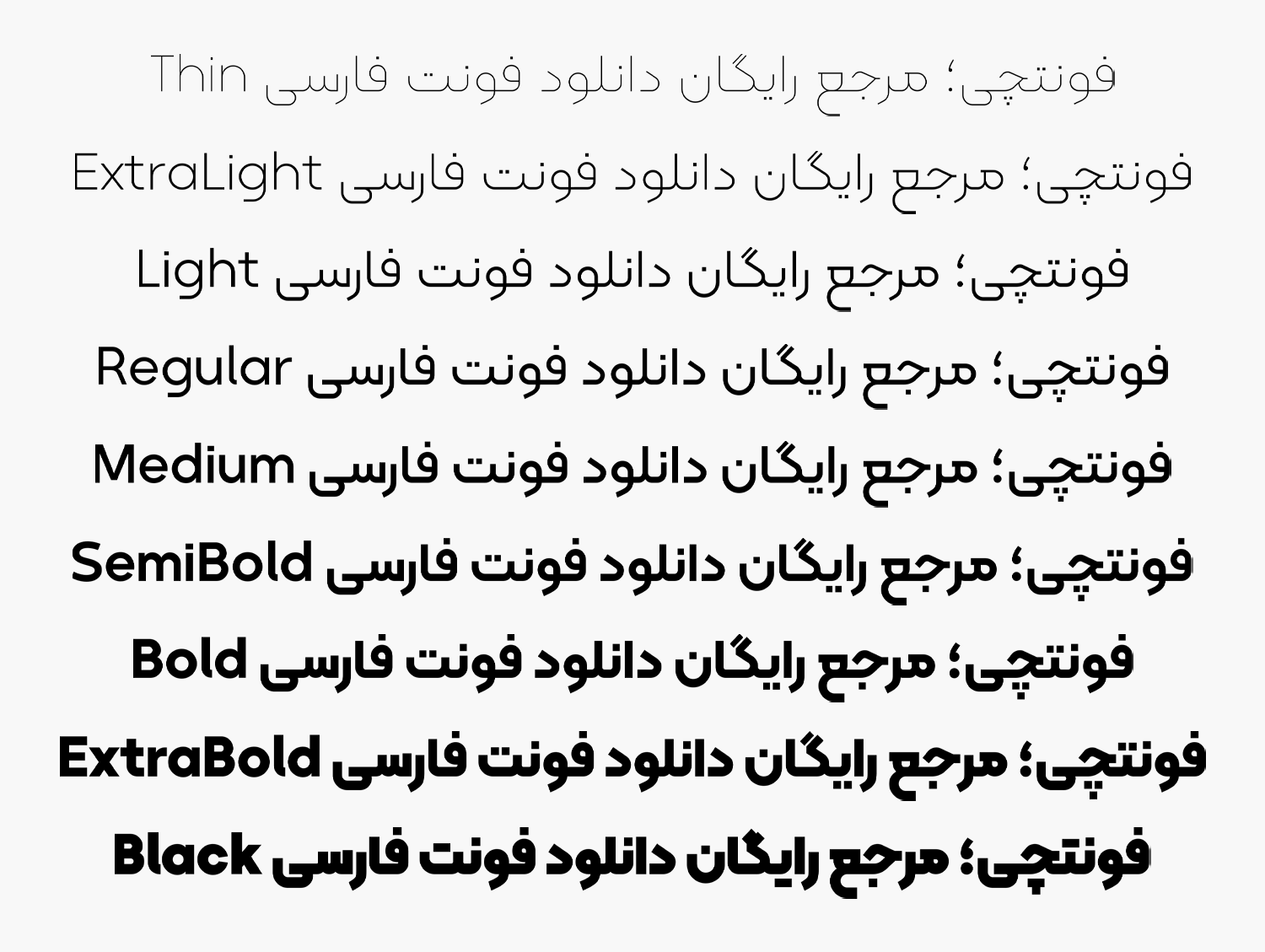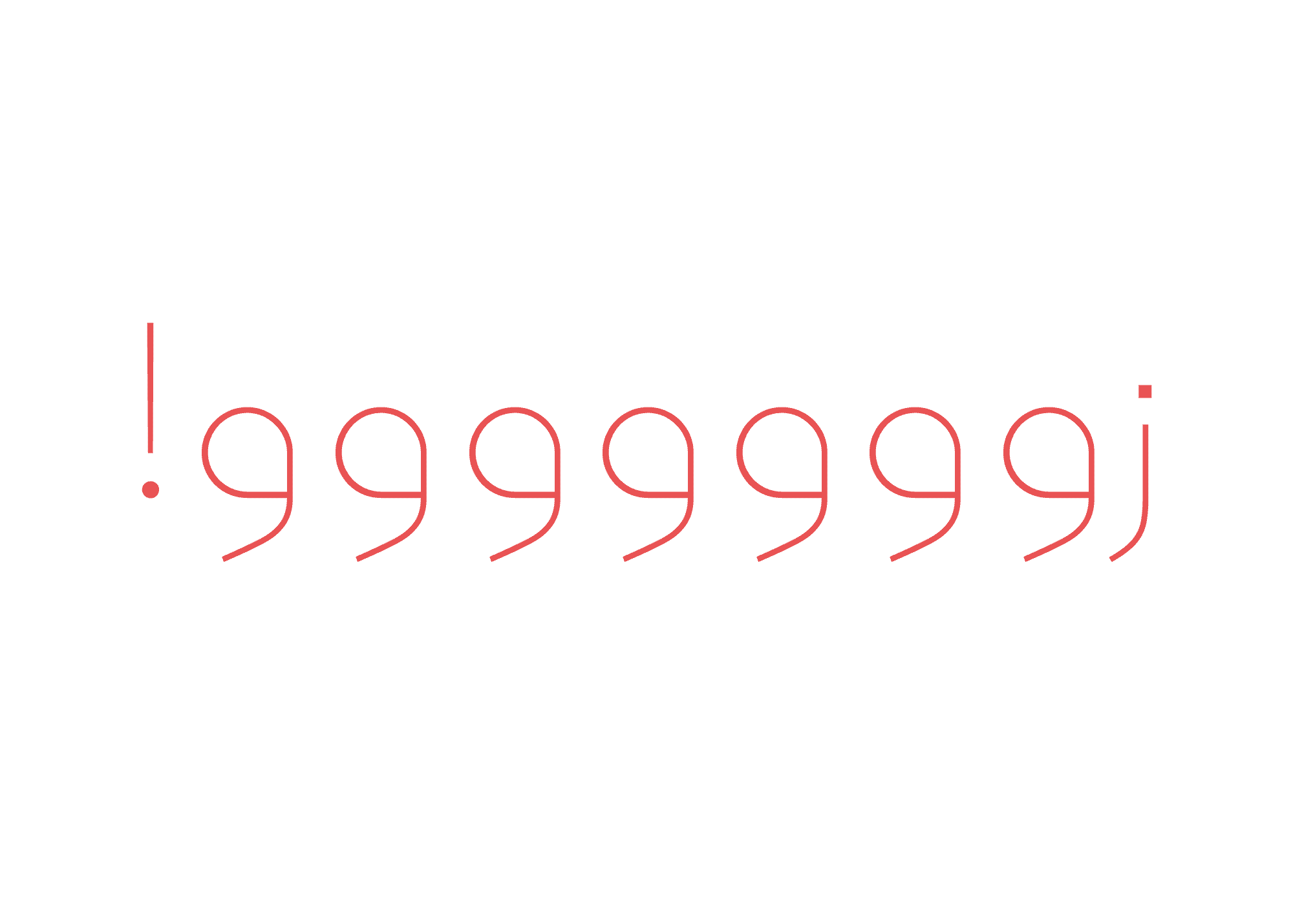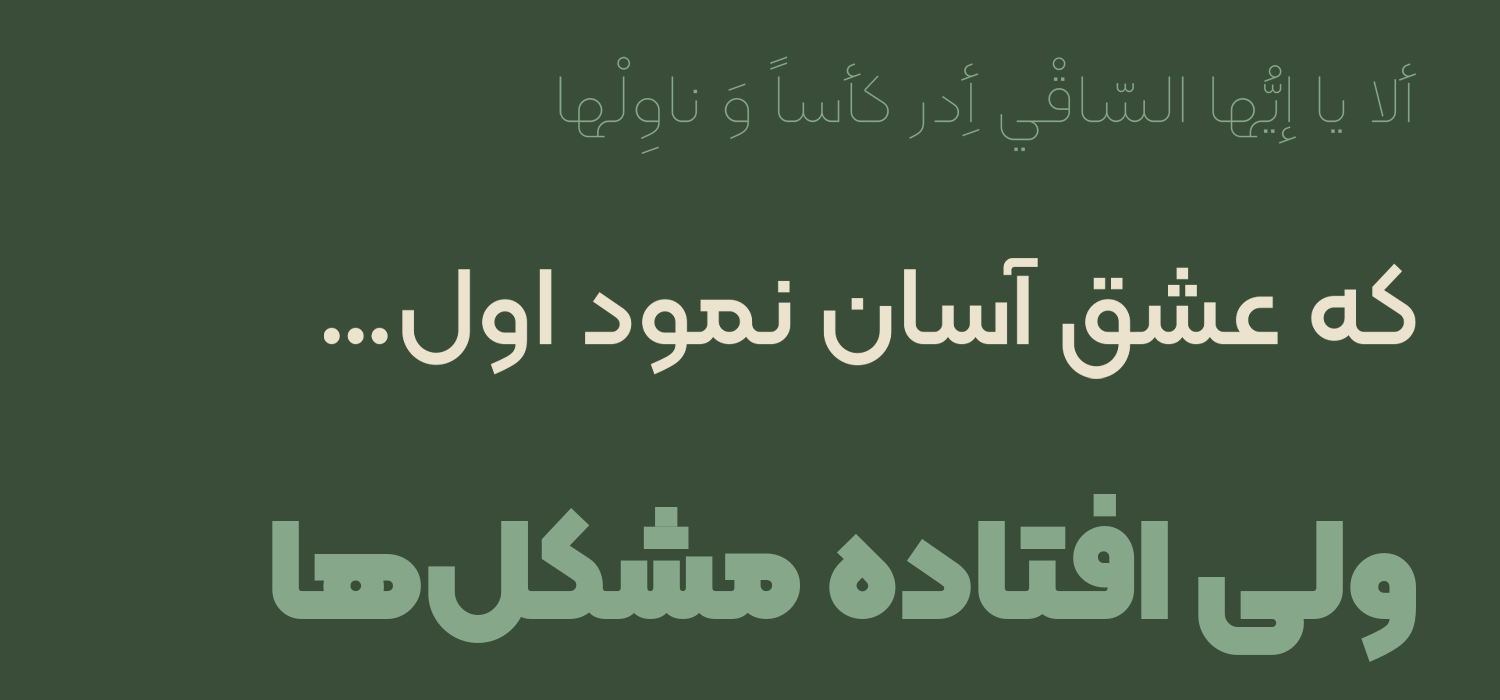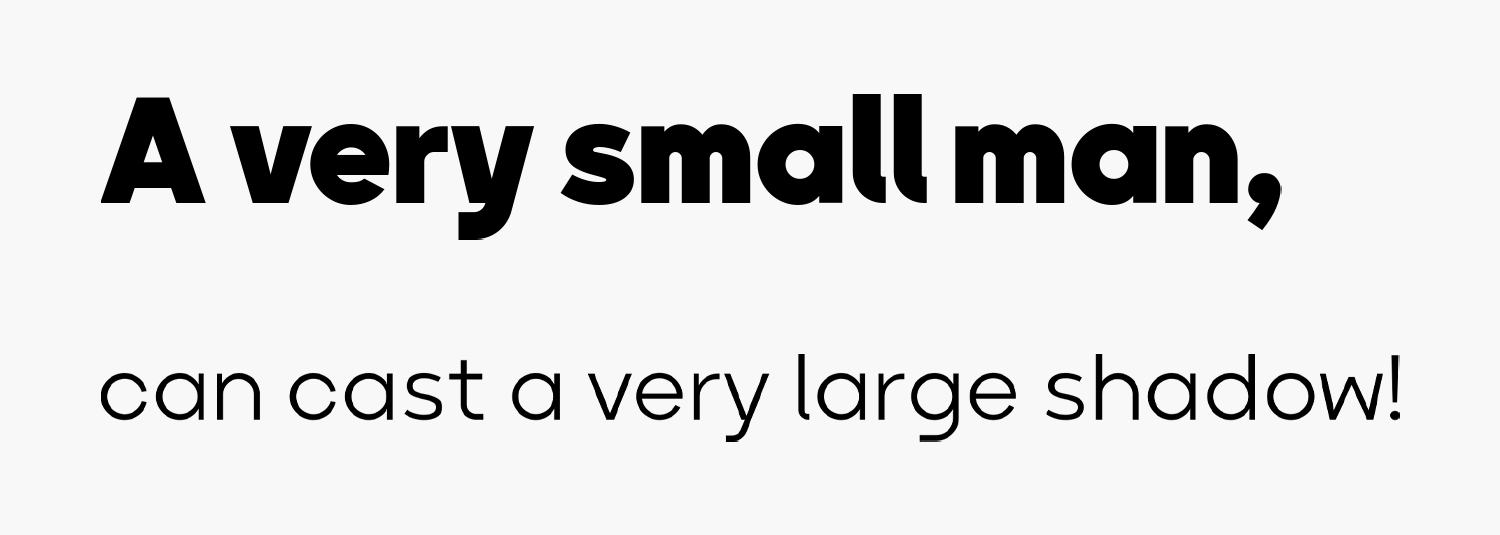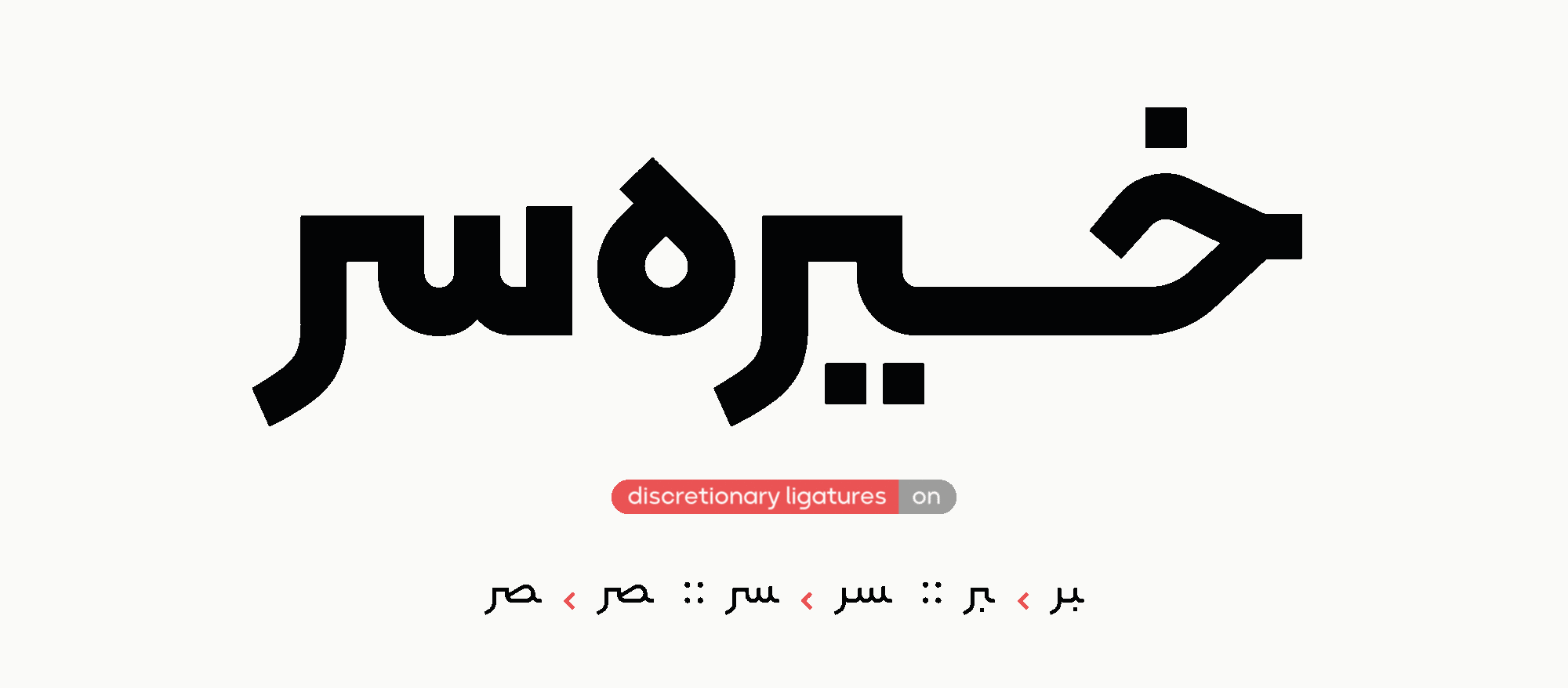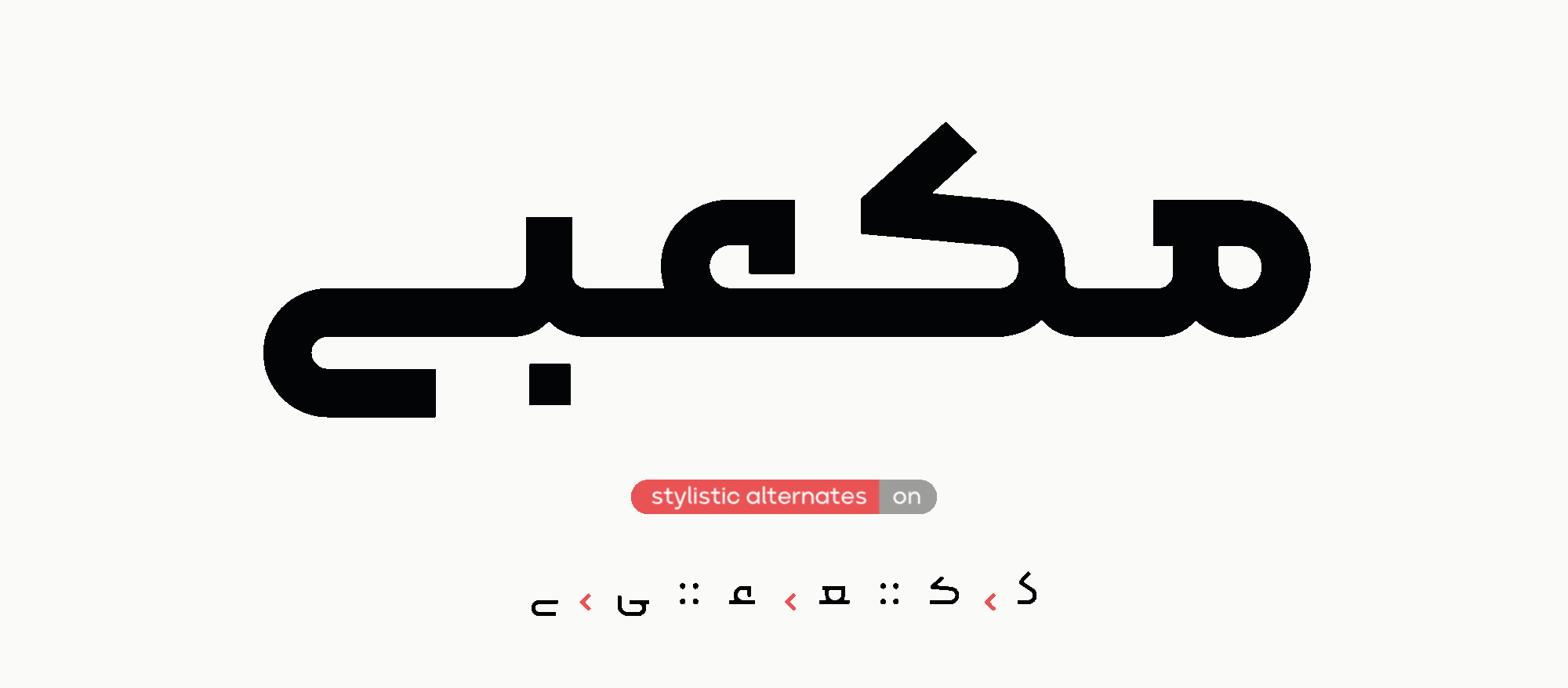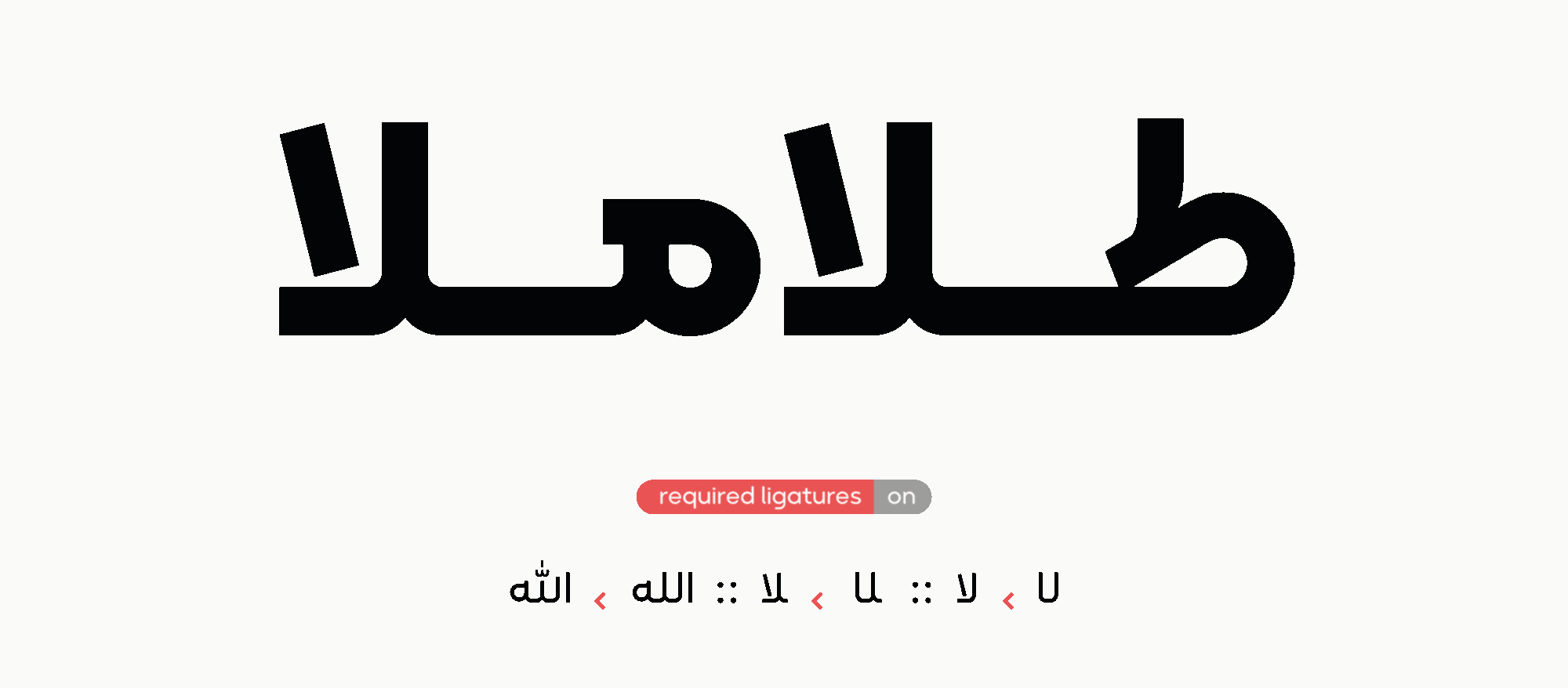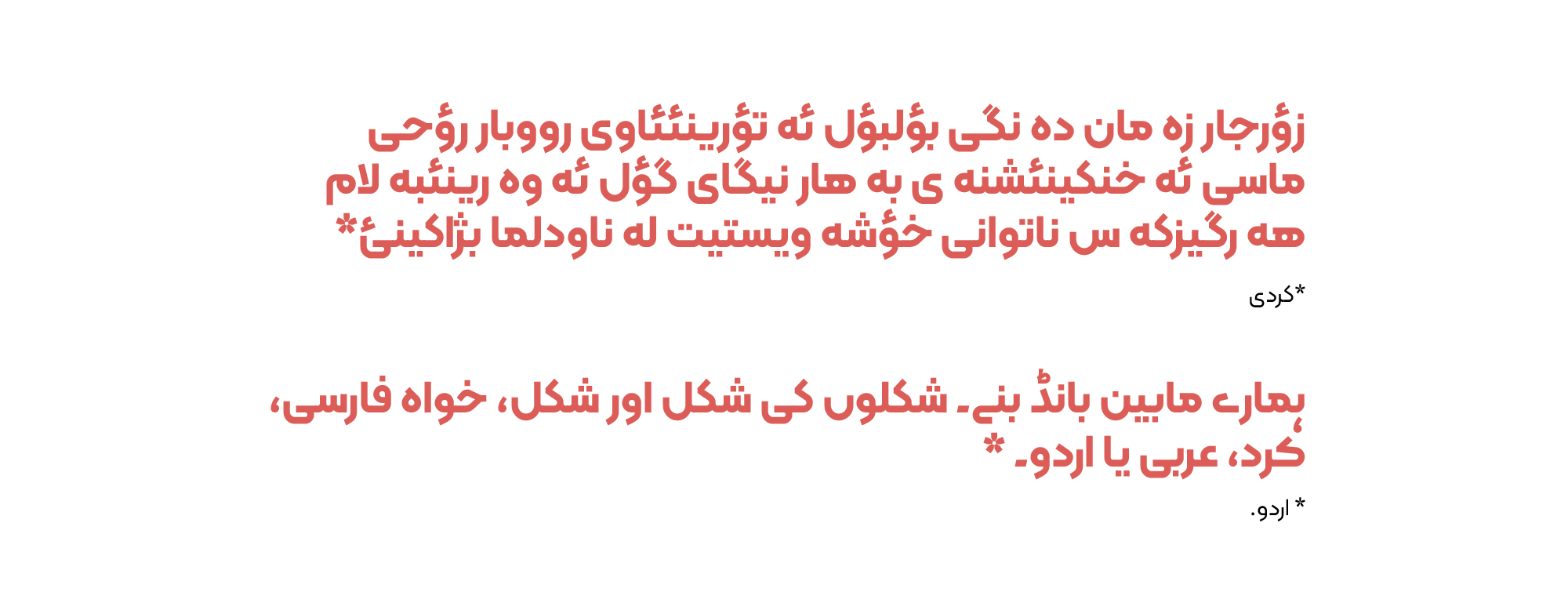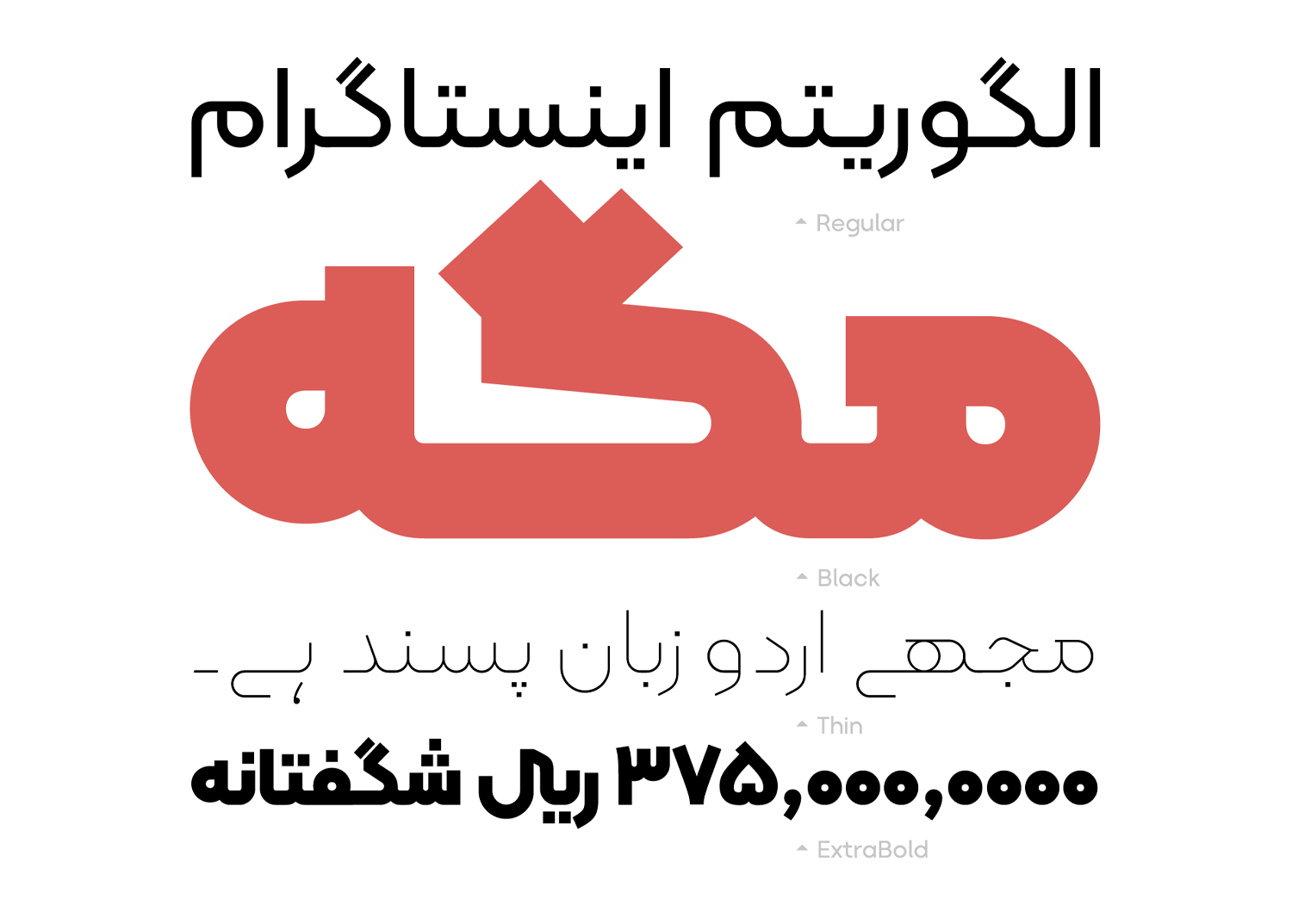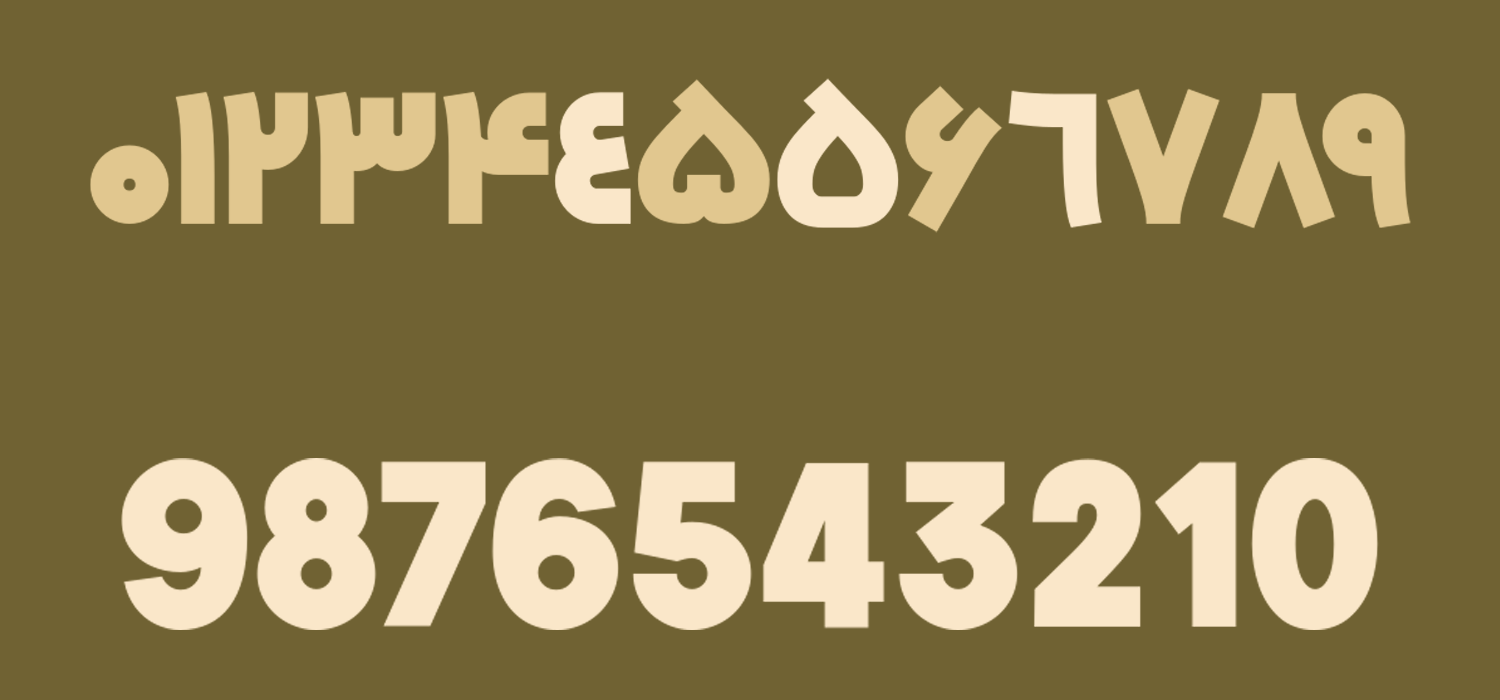
فونت کلمه (Kalameh)
| نام | کلمه |
| نام نمایشی | kalameh |
| طراح | سید ناصر خادم |
فونت کلمه (به انگلیسی: Kalameh) در گروه فونتهای هندسی قرار دارد که میتوانید از آن در متنهای کوتاه یا بلند استفاده کنید. عمده کاربرد این قلم میتواند برای تبلیغات، طراحی پوستر و فضاهایی باشد که نیاز به فونتی با ساختار گرد و منحنیشکل داشته باشید. فونت کلمه رایگان نیست و شامل ۳ بسته در ۹ وزن مختلف است.
طراحی فونت کلمه توسط ناصر خادم صورت گرفته است که با در کنار هم قرار گرفتن منحنیهایی از حروف این قلم را با یک ساختار هندسی نسبتا فشرده طراحی کرده است.
در ادامه این نوشته از سایت فونتچی به نقد و بررسی فونت کلمه خواهیم پرداخت؛ قلمی که با پشتیبانی از ۹ وزن مختلف نازک تا سیاه میتوانید از آن برای فونت عنوان و متن استفاده کنید.
بررسی و دانلود فونت (Kalameh)
فونت کلمه، ساختاری هندسی و منظم دارد. استخوانبندی اندام این قلم فضایی شسته و رفته را مهیا میکند. پویایی و انرژی فونت کلمه، برای استفاده در اکثر آثار تبلیغاتی بهویژه برای استارتاپها و کسبوکارهای خلاق و نوین بسیار مناسب است؛ چرا که یک قلم هندسی با ساختاری مدرن و معاصر است.
فونت کلمه، قدرتمند و خودنماست؛ در متنهایی که تلاش دارند ویژگیها و تواناییهای خاصی را برجسته کنند و نکات طلایی موضوع را شاخص نمایند، “کلمه” این قدرت را به آنها فراهم میکند.
این فونت ضخیم شباهت زیادی به فونت ایران یکان دارد و شاید در نگاه اول آنها را اشتباه تشخیص دهید. ظاهری ضخیم و جدی که میتوانید از آن برای عنوان کتاب و مجلات، طراحی بنرهای تبلیغاتی و موضوعات مختلف دیگری که نیاز به یک فونت نمایشی دارید استفاده کنید.
سبک طراحی و وزن فونت کلمه
کلمه قلمی دارای ظاهری نرم و دوستانه است که با توجه به سبک طراحی و وزنی که به ما میدهد، در گروه فونتهای سیاه دستهبندی میشود. این قلم بیشتر برای استفاده در فضای تبلیغات مناسب است؛ اما میتوان از آن در وب فونت، فونت موبایل و فونت مطبوعات، بهویژه طراحی انواع پوستر و جلد کتاب نیز استفاده کرد.
پشتیبانی از ۵ زبان متنوع
فونت کلمه علاوه بر زبان فارسی از زبانهای دیگر بر پایه این رسم خط پشتیبانی میکند. پشتیبانی این قلم شامل زبان عربی، اردو و کردی است که علاوه بر حروف مشترک، حروفی که تفاوت جزئی دارند را نیز برای هر زبان پشتیبانی میکند. حروفی مانند «ك، ي، ة، ؤ، ئ» در عربی که تفاوت جزئی دارند یا حروف «ﮧ، ﮩ، ے» در اردو پیاده سازی شده است.
اعراب و گلیفهایی هم که جنبه تزئینی دارند در این قلم پیادهسازی شده است که میتوانید به صورت استاندارد از آنها استفاده کنید.
این قلم نیز از زبان انگلیسی پشتیبانی میکند که کلیه حروف و کاراکترهای این زبان نیز به همان سبک زبان فارسی طراحی شده و از قلم یا فونت اپنسورس دیگری وام گرفته نشده است.
دارای ترکیبات و حروف جایگزین
ویژگی دیگر فونت کلمه پشتیبانی از ترکیبات و حروف جایگزین است که امکان تایپ کلمات را در شکلهای مختلفی برای برخی حروف و ترکیبات دوتایی میدهد. به عنوان مثال در کلمه «خیرهسر» مشابه تصویر زیر میبینید که ترکیب «ـر» با دو حالت قابل تایپ است. میتوانید چنین ترکیبی را در ترکیبات «ـبر، ـسر، ـشر، ـصر، ـضر» استفاده کنید.
دیگر ترکیبات این فونت حروف تکی هستند که مانند نمونه زیر میتوانید، حروف «ک، گ، ـعـ، عـ، ی، ـی» را در چند حالت زیر تایپ کنید.
یک سری ترکیبات نیز مانند «لا» وجود دارند که مشابه زیر میتوانید در کلماتی خاص استفاده کنید تا حالت تایپ خاصی را داشته باشید.
دارای گلیف های تزئینی و ریال
قابلیت دیگر فونت کلمه پشتیبانی از گلیفهای تزئینی و خاص است. در این قلم میتوانید برای زبان کردی و اردو که سرشار از گلیفهای تزئینی که گاها جنبه اعراب نیز دارند بر روی حروف استفاده کنید. همانطور که در تصویر زیر نمونهای از آن را میبینید.
گلیف دیگر این قلم شامل گلیف ریال است که میتوانید برای واحد پولی در حالتی که از این قلم با هدف تبلیغات استفاده کنید که تاثیر مناسبی روی جلب توجه مخاطب خواهد گذاشت.
هر چند که انتظار میرود با توجه به روانشناسی قیمتگذاری بهتر، گلیف «تومان» نیز در آپدیتهای بعدی این قلم افزوده شود.
فونت کلمه فارسی همراه با اعداد عربی
این قلم دارای پشتیبانی استاندارد از اعداد زبانهای اصلی که شامل فارسی، عربی و انگلیسی است میباشد. در هر زبان میتوانید اعداد همان زبان را تایپ کنید.